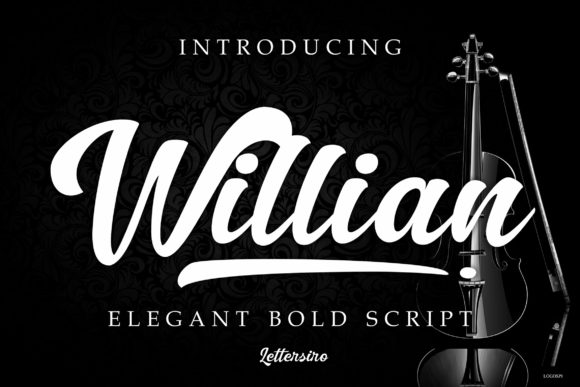
Willian Script
การค้นหาองค์ประกอบการออกแบบที่เหมาะสมอาจเป็นเรื่องท้าทาย แต่ Willian Script นำเสนอคอลเลกชันที่โดดเด่นซึ่งช่วยยกระดับงานของคุณได้ทันที
สร้างขึ้นอย่างแม่นยำ Willian Script ให้เวกเตอร์ที่สะอาด พิมพ์ตัวอักษรที่ราบรื่น และใบอนุญาตเชิงพาณิชย์เพื่อความสบายใจ
ไม่ว่าคุณจะสร้างผลิตภัณฑ์ POD (Print on Demand) คำเชิญงานแต่งงาน หรือกราฟิกโซเชียลมีเดีย Willian Script ก็เหมาะสมอย่างยิ่ง